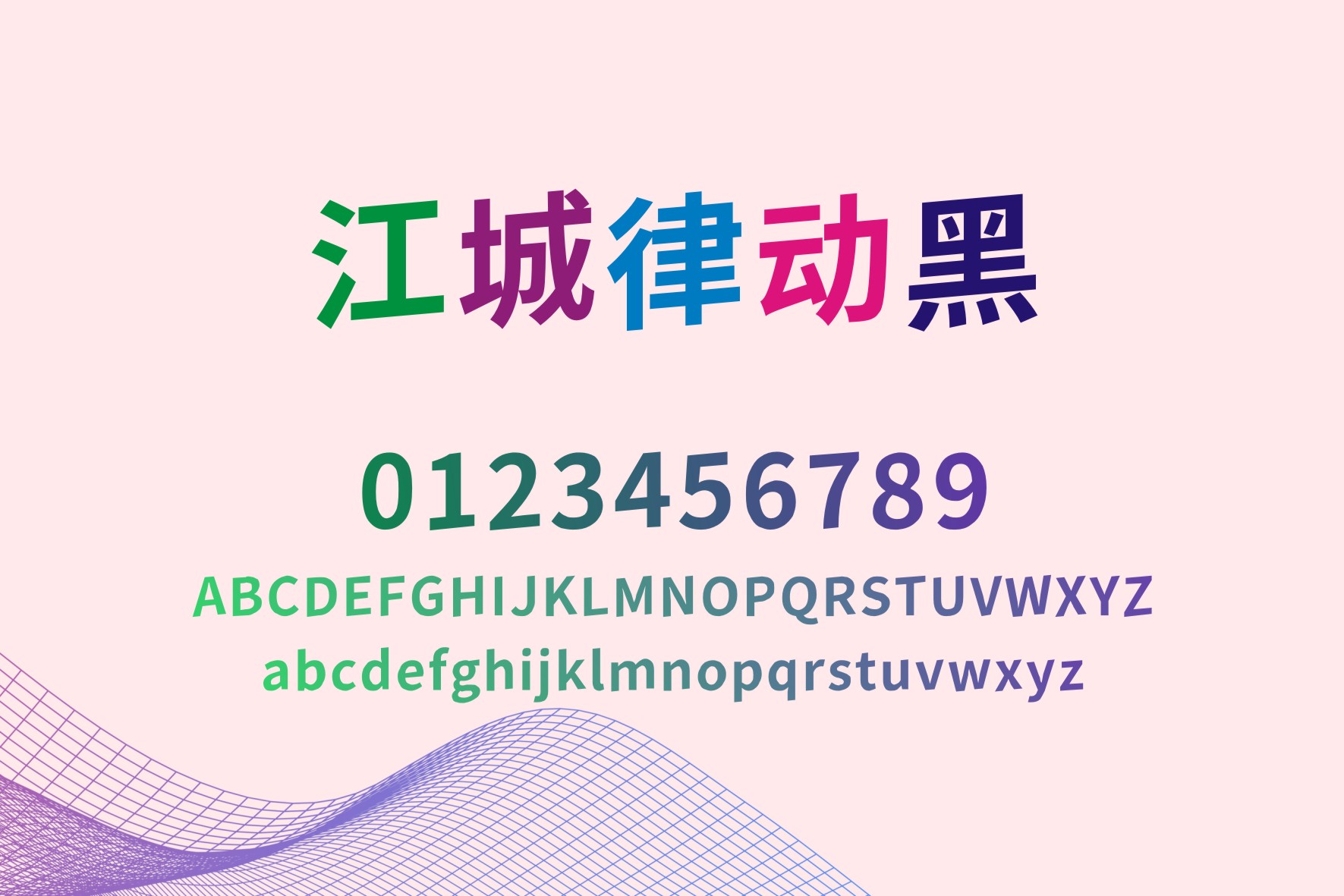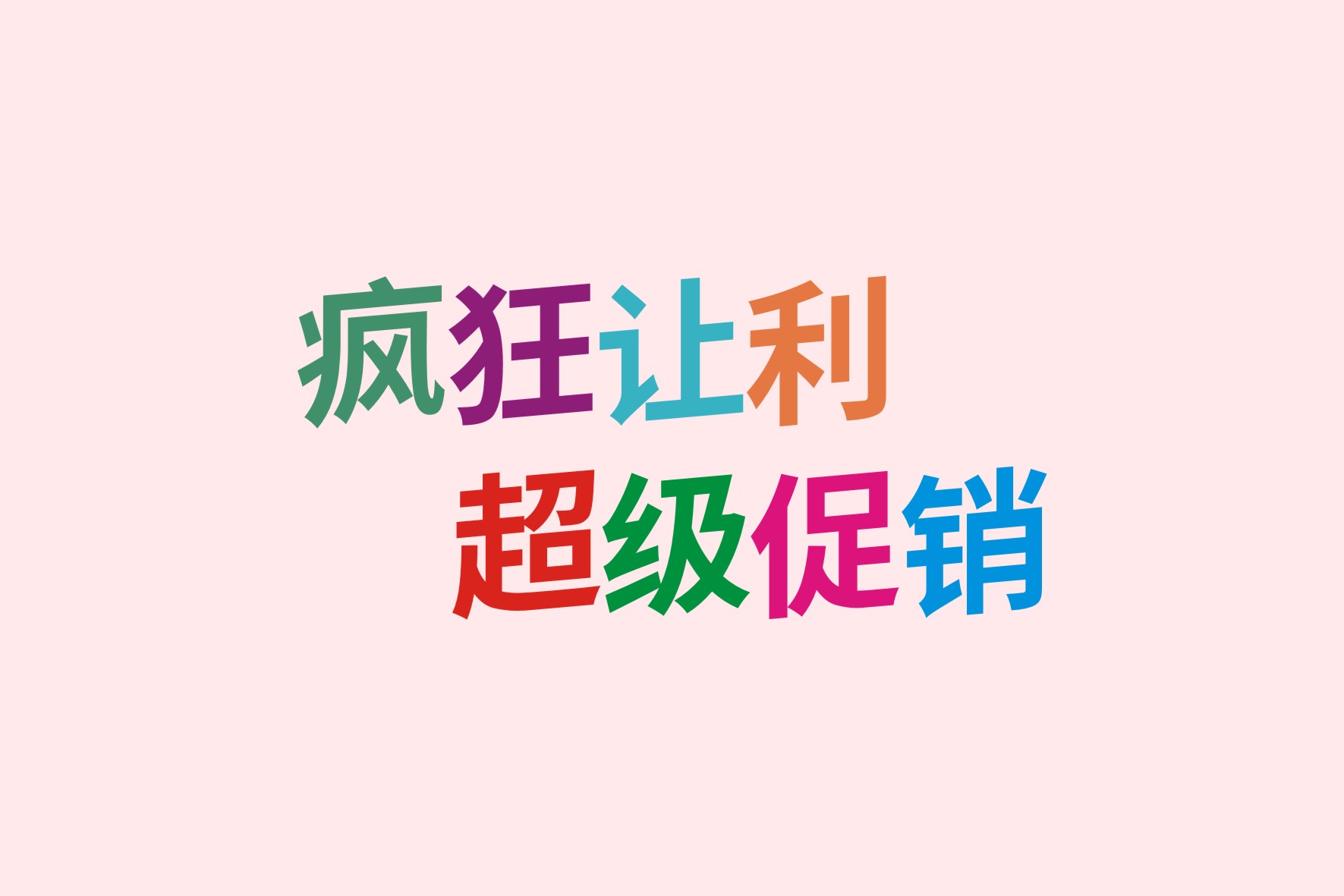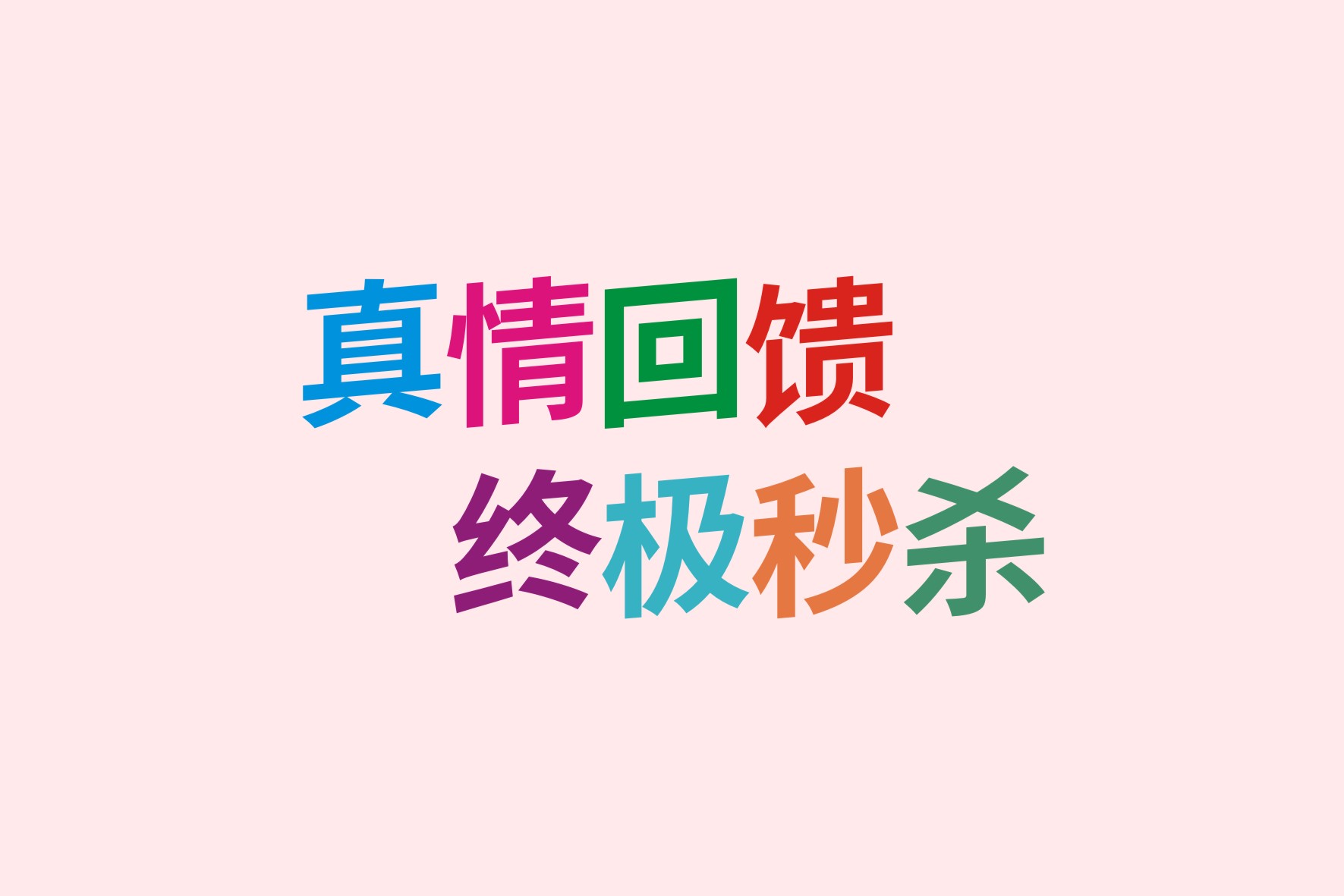
字体名称: 江城律动黑
江城律动黑
江城律动黑介绍
基于思源黑体-Bold向上倾斜5度改造,字体向上倾斜,上下律动,自带活动促销BGM,天生适用于活动、促销等广告语,适当缩小字间距效果更佳哦。
江城律动黑字体JiangChengLvDongHei字库是一款让人赏心悦目、百看不厌的中文字体,适合各类广告和产品包装设计应用,字体大小17.72MB,格式为ttf字体,上传用户是舒甜咖啡,作者/版权方为刘鹏
江城律动黑效果图